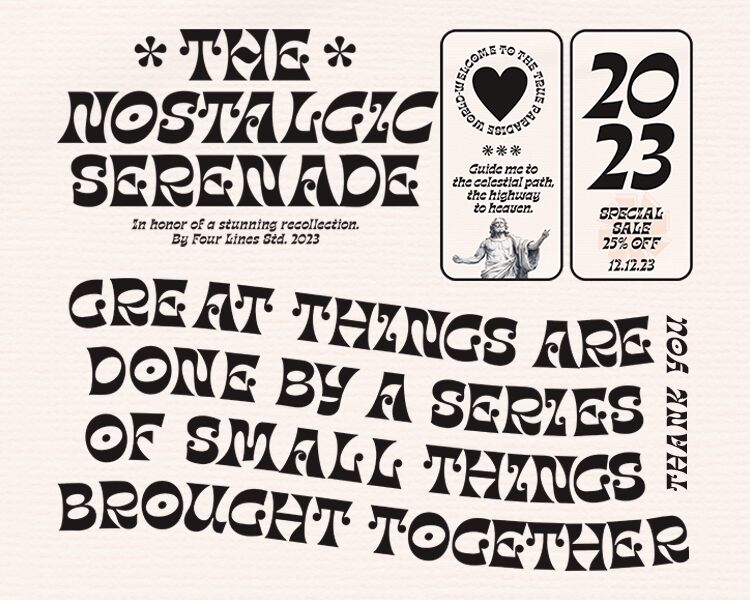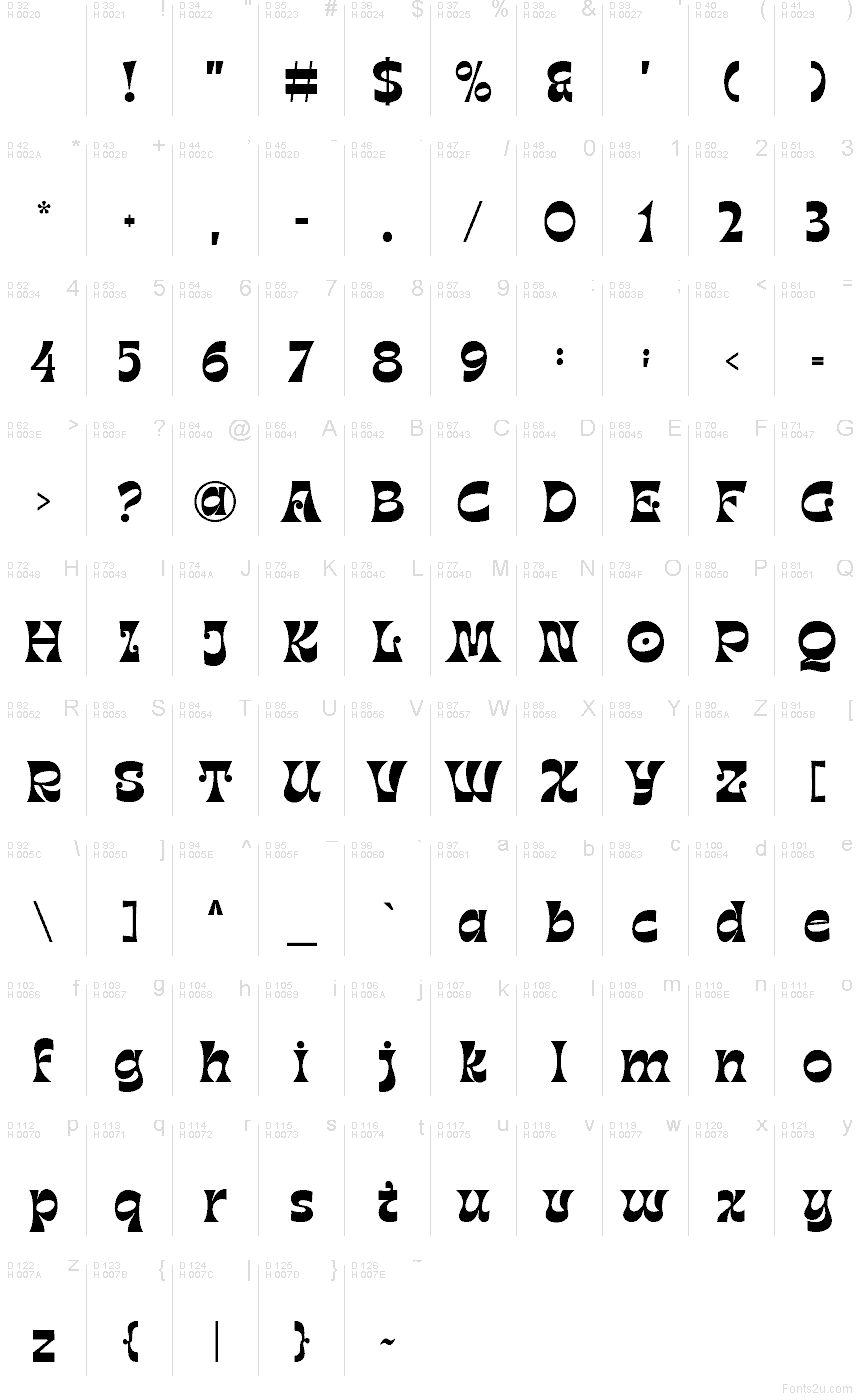
Nostalgic Serenade
Nostalgic Serenade par Four Line Std est une police de caractères display groovy gratuite, caractérisée par des formes arrondies et fluides ainsi qu'un rythme rétro décontracté. Ses lettres mêlent courbes douces et angles plus vifs, offrant au design une esthétique inspirée des années 70, sans jamais paraître trop chargée.
Nostalgic Serenade est parfaite pour les pochettes d'albums, les titres d'affiches, les menus de cafés, les logos et les visuels de réseaux sociaux qui demandent une touche vintage chaleureuse. Ses courbes souples et ses formes distinctives apportent un ton nostalgique affirmé aux packagings, cartes d'invitation, couvertures et textes d'affichage courts.